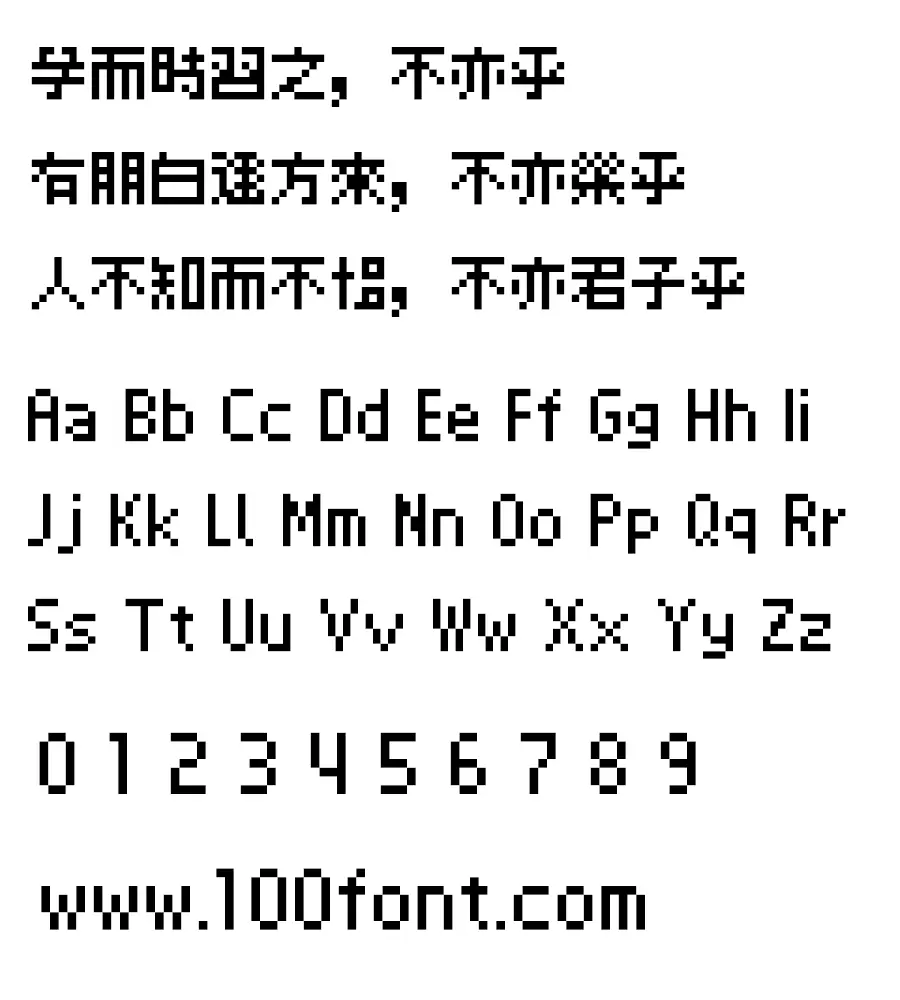
Galmuri 是一種位圖字體,其靈感來自任天堂 DS 控制檯和軟件中使用的字體設計。它於 2019 年 10 月 9 日的韓文日首次發佈,Galmuri 的名稱來源於“ Galmuri M ”,這是一種位圖字體,由 Kim Dong-han 於 2008 年 6 月在用戶韓語化社區Hansikgu創建和分發。
Galmuri14 在 15px (11pt) 時最清晰,Galmuri11 在 12px (9pt) 時最清晰,Galmuri9 在 10px (7.5pt) 時最清晰,而 Galmuri7 在 8px (6pt) 大小和倍數時最清晰。
Galmuri는 닌텐도 DS 본체와 소프트웨어에 사용되었던 폰트 디자인에서 영감을 받은 비트맵 폰트입니다. 2019년 10월 9일 한글날에 처음 공개되었으며, Galmuri의 이름은 2008년 6월 사용자 한글화 커뮤니티인 한식구에서 김동한 님께서 만들어 배포하신 비트맵 폰트 ‘갈무리M’에서 유래하였습니다.
Galmuri14는 15px (11pt), Galmuri11은 12px (9pt), Galmuri9는 10px (7.5pt), Galmuri7은 8px (6pt) 크기와 그 배수에서 가장 명확하게 표시됩니다.